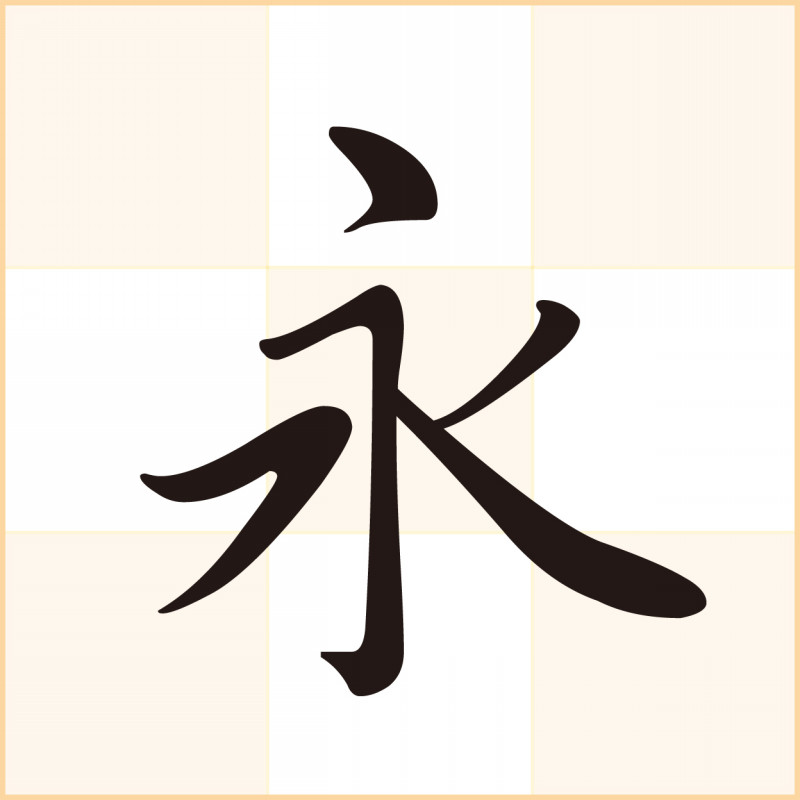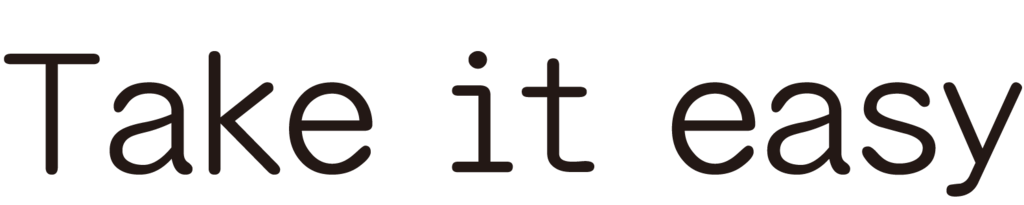
流れるように続けて書く画法が躍動感を感じさせる書体「行書体」
流れるように続けて書く画法が躍動感を感じさせる書体。画像はダイナコムウェアが開発・販売しているDF行書体。
DF行書体の組見本(W3)
欧文・数字は丸ゴシック体になっている。
新元号「令和」行書体書体見本
新元号「令和」の行書体の書体見本。